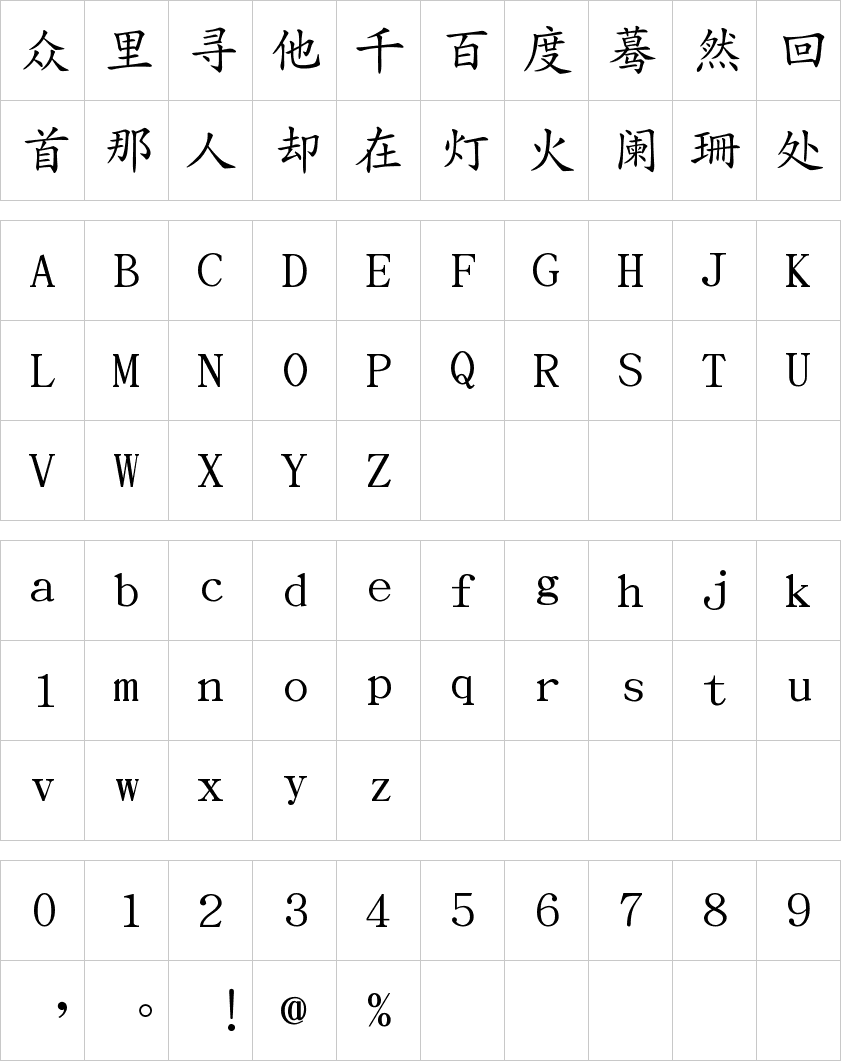
文鼎AR PL UKai
文鼎UKai字体的真正名称是“AR PL UKai”,只是因为只有英文名称会让大家以为这款字体是一款英文字体,所以为了方便大家记忆和比较容易做预览图,猫啃网强行帮这款字体加了个中文名称“文鼎”。而事实上猫啃君并没有对这款字体作出任何修改,字体名称依然是“AR PL UKai”。
这是一个高质量的中国Unicode TrueType字体集合,它来自于“文鼎PL中楷体(BIG5)”和“文鼎PL简中楷”字体,由文鼎科技在“文鼎公众授权”下慷慨地提供给自由软件社区。
它已从原来的“文鼎PL中楷体(BIG5)”和“文鼎PL简中楷”字体中扩展而来,增加了现已覆盖ISO 8859-1,2,3,4,9,10,13,14,15,BIG 5,GB 2312-80和HKSCS-2004的字体。它还包括根据Unicode 5.0标准为客家和闽南提供的Bopomofo扩展及其MBE变体。
这种字体还包括萤火虫的位图字符,以更好地渲染小字体(BIG 5和GB 2312)。